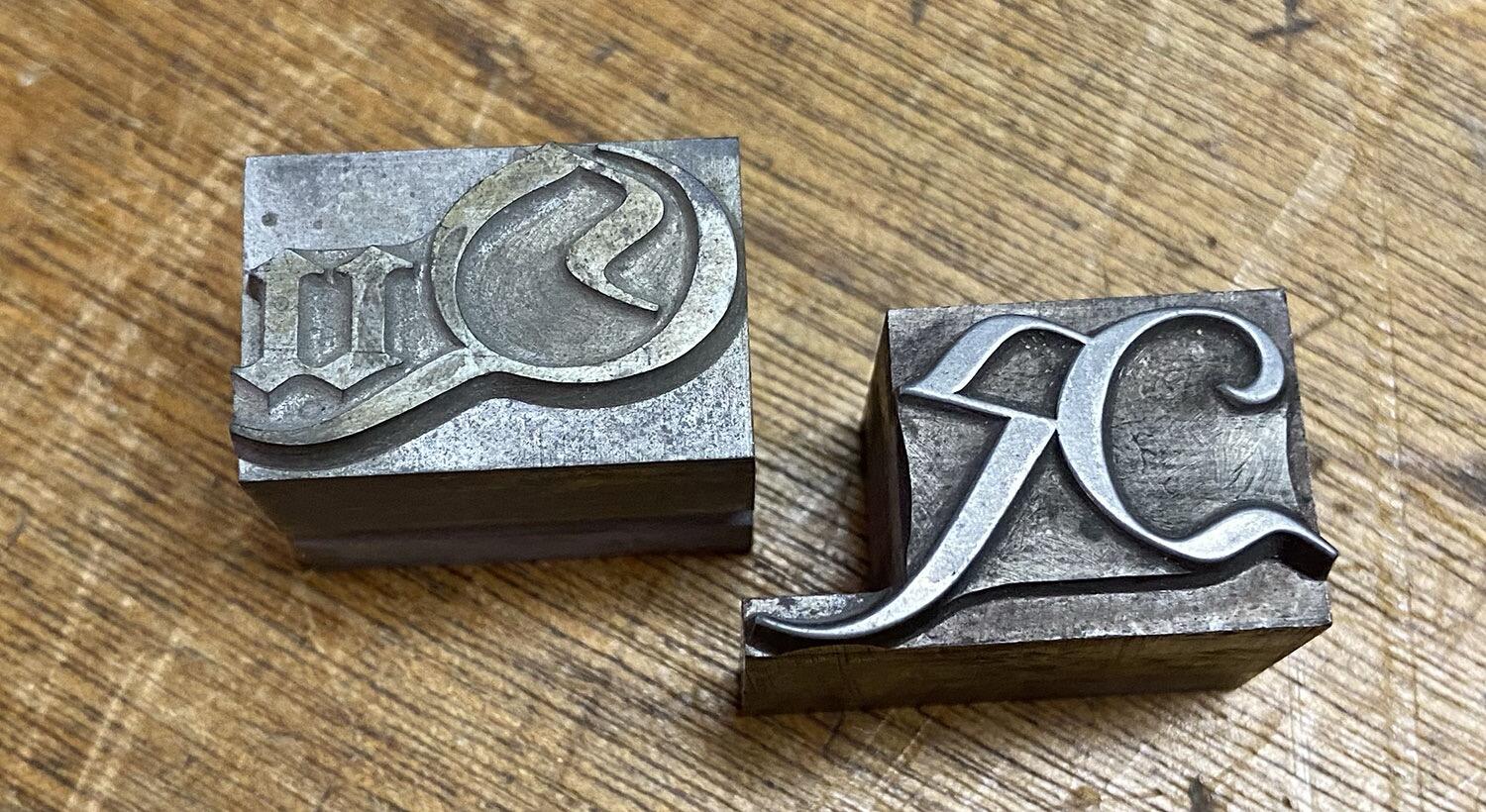
(EB)Garamond: Das lange Q im Bleisatz
Ich bin ein großer Fan der Garamond, die ich eigentlich immer in der EBGaramond-Digitalisierung von Georg Mayr-Duffner nutze. Eine der »Spezialitäten« dieser Schrift, die mir gut gefällt, ist das »langschwänzige« große Q, dessen Schwanz in Wörtern wie »Qualle« bis ans Ende des kleinen A reicht. Dass es diesen Buchstaben auch schon zu Zeiten des Bleisatzes gab, wird zum Beispiel aus dieser Grafik deutlich:
Meine Frage: Wie wurde das gesetzt? Gab es Ligaturen mit Buchstabenfolgen wie »Qua« und »Que«?
Es gibt beides. Herausgeschnittene Schwünge, die mit passenden Kleinbuchstaben übersetzt werden müssen (siehe R) und Ligaturen (Qu). Letzteres ist zumindest für deutsche Schriften wohl die üblichere Variante. Dem Q folgt ja bei uns immer ein u.